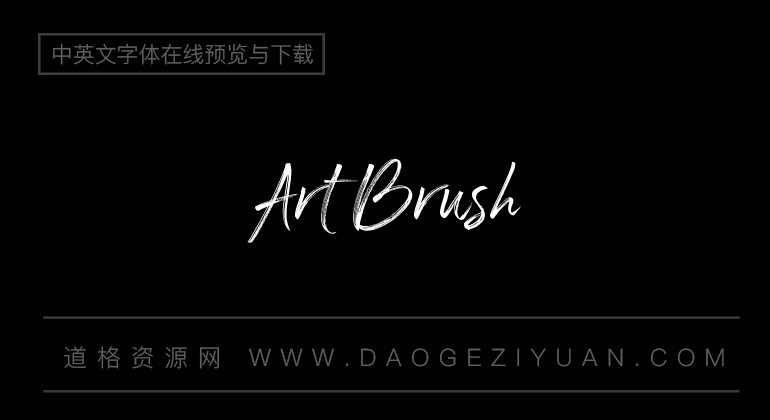
Art Brush
? Art Brush 字体是一种特殊的字体,它可以模拟画笔的自然笔触,并可以调整字体的宽度和粗细度。Art Brush 字体可以为文字添加更多的艺术性,使文字更有表现力。它可以帮助设计师更好地表达他们的想法,使文字更加有趣,更有视觉吸引力。
Art Brush是一款非常不错的手写艺术字体,具有很好的视觉感,适合于文化类的宣传设计、商业类品牌的广告和产品包装设计以及个性化文字排版等较多场景。
Art Brush字符映射图